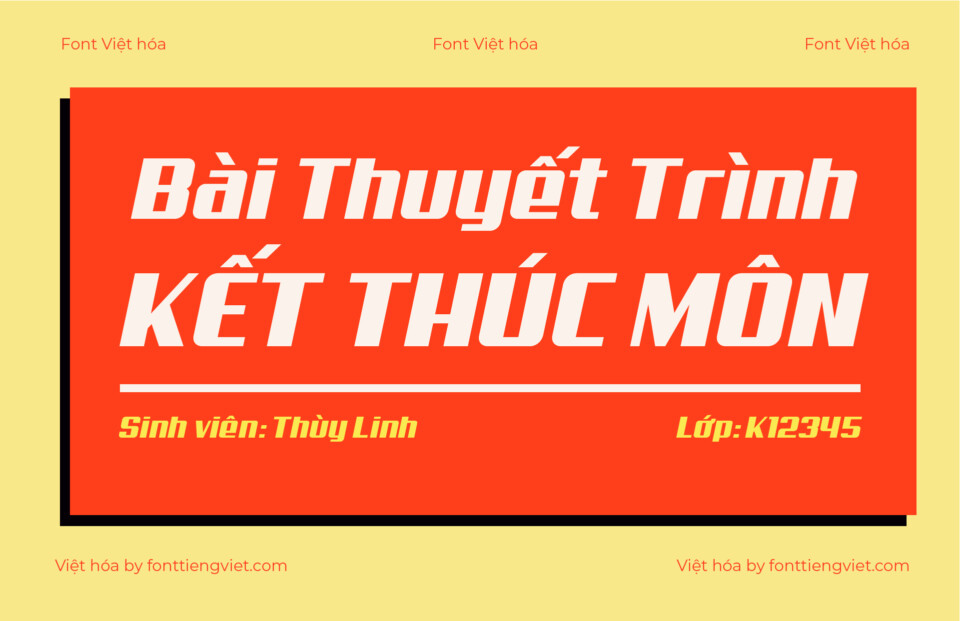
Font Việt hóa 1FTV VIP Aero
Font Việt hóa 1FTV VIP Aero – Lựa chọn hàng đầu cho thiết kế hiện đại
Giới thiệu về Font Việt hóa 1FTV VIP Aero
Trong thế giới thiết kế đồ họa ngày nay, việc lựa chọn một bộ font chữ phù hợp đóng vai trò quyết định đến sự thành công của một sản phẩm truyền thông. Font Việt hóa 1FTV VIP Aero nổi lên như một giải pháp hoàn hảo cho những ai đang tìm kiếm sự kết hợp giữa nét hiện đại, tinh tế và khả năng hiển thị tiếng Việt mượt mà. Đây là bộ Font Miễn Phí được tinh chỉnh kỹ lưỡng để phục vụ cộng đồng designer Việt Nam, giúp xóa bỏ hoàn toàn lỗi gõ dấu khó chịu trên các phần mềm thiết kế phổ biến. Với cấu trúc nét thanh thoát nhưng vẫn giữ được độ dày dặn cần thiết, bộ font này mang đến cảm giác chuyên nghiệp, năng động và tràn đầy cảm hứng cho người xem ngay từ cái nhìn đầu tiên.
Ưu điểm nổi bật của Font Việt hóa 1FTV VIP Aero
Thiết kế linh hoạt và đa dụng
Đặc điểm nổi bật nhất của Font Việt hóa 1FTV VIP Aero chính là tính ứng dụng cực kỳ cao trong nhiều lĩnh vực khác nhau. Từ việc thiết kế ảnh bìa cho các bài thuyết trình tại trường học, trình bày tài liệu giảng dạy cho giáo viên đến việc sáng tạo nội dung trên mạng xã hội, bộ font này đều đáp ứng tốt. Các ký tự được thiết kế với độ rộng vừa phải, tạo khoảng cách hợp lý giúp người đọc không bị mỏi mắt khi theo dõi các đoạn văn dài. Đặc biệt, bộ font này hỗ trợ đầy đủ hệ thống bảng mã tiếng Việt, đảm bảo tính thẩm mỹ cao nhất cho mọi văn bản.
Tương thích tốt với mọi nền tảng
Ứng dụng Font Việt hóa 1FTV VIP Aero vào thực tế
Việc sử dụng Font Việt hóa 1FTV VIP Aero trong các dự án sáng tạo sẽ giúp nâng tầm giá trị hình ảnh của bạn. Đối với môi trường học đường, font chữ này cực kỳ phù hợp để làm tiêu đề cho các báo cáo khoa học, làm poster sự kiện trường học hoặc trang trí bảng tin lớp. Những đường nét mạnh mẽ của nó giúp thông điệp truyền tải rõ ràng hơn, thu hút sự chú ý của mọi người một cách tự nhiên. Bên cạnh đó, nếu bạn đang thực hiện các dự án cá nhân như làm thiệp chúc mừng, in ấn áo đồng phục hay làm video blog, đây cũng là một lựa chọn không thể bỏ qua để tạo nên dấu ấn riêng biệt.
Kết luận về bộ Font Việt hóa 1FTV VIP Aero
Tóm lại, Font Việt hóa 1FTV VIP Aero là một công cụ hỗ trợ đắc lực không thể thiếu trong kho tài nguyên của mỗi người làm sáng tạo. Với những ưu điểm về mặt thẩm mỹ lẫn tính năng kỹ thuật, bộ font này chắc chắn sẽ làm hài lòng cả những người dùng khó tính nhất. Hãy nhanh tay trải nghiệm và chia sẻ nguồn tài liệu Font Miễn Phí, Font Việt Hóa, Font Việt hóa 1FTV VIP Aero này đến bạn bè để cùng nhau tạo nên những tác phẩm ấn tượng. Việc sử dụng font chữ đúng cách không chỉ thể hiện sự tôn trọng người xem mà còn là minh chứng cho sự chỉn chu, chuyên nghiệp trong phong cách làm việc của bạn mỗi ngày.